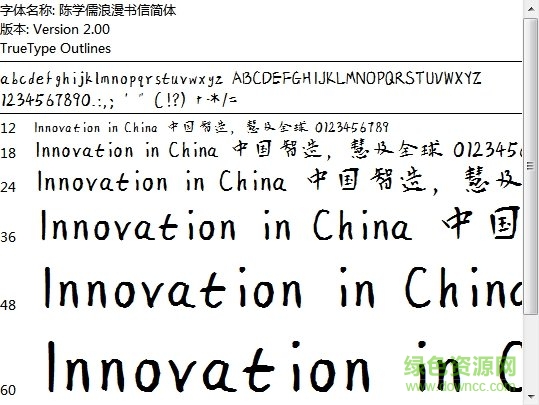
陳學儒浪漫書信字體是一款字跡清新質(zhì)樸的情書字體,出自著名書法家陳學儒執(zhí)手,字跡頗有古風飄逸灑脫之風韻,造型形散神不散,十分出色,綠色資源網(wǎng)今日推薦!
陳學儒書信字體整體風格大氣婉約,有著毛筆書法字體的蓬勃之勢,也有著手寫字體的干練簡潔,藝術(shù)效果極佳,給你的手機字體閱讀、平面設(shè)計、海報創(chuàng)意等都帶來不錯的體驗!
陳學儒,男,祖籍廣東省羅定市,文化中國網(wǎng)簽約書畫家、中國工程機器人大賽技術(shù)委員。本科學歷,清華大學重點中學師資提升計劃培訓班結(jié)業(yè)。書畫作品多次獲全國、省市級比賽一、二等獎。曾擔任長沙市第九屆雛鷹杯青少年書畫攝影大賽特邀評委、教育部藝術(shù)教育委員會主辦的第十三屆全國中小學生書畫比賽東莞賽區(qū)評委、深圳市教育局主辦的第三、四屆“雛鵬獎”微電影大賽評委。曾被共青團東莞市委員會授予“東莞市網(wǎng)絡文明使者”稱號,獲深圳市教育局2016、2017“雛鵬獎”微電影大賽年度先進個人稱號、獲清華大學教育研究院主辦的科技學術(shù)競賽優(yōu)秀指導教師獎、中國教育電視臺等單位授予的優(yōu)秀制作獎等多個獎項。書畫作品多次應邀在省級期刊發(fā)表。其書畫作品多幅被市政府、博物館、國際友人、華僑等單位及個人收藏,極具收藏價值。深圳特區(qū)報、深圳晶報、寶安日報、南方教育時報、搜狐網(wǎng)等媒體均有其相關(guān)報道。